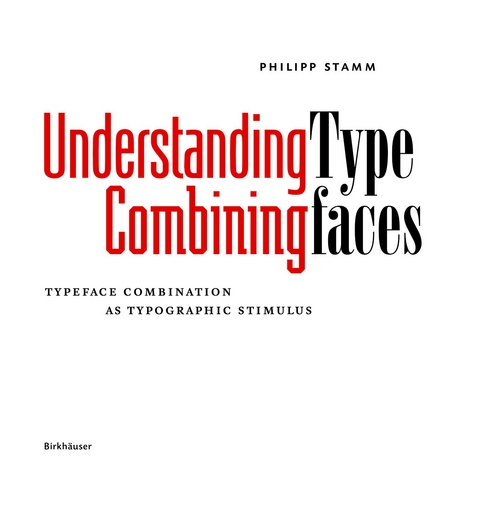
Understanding – Combining Typefaces
Typeface combination as a stimulus in typography
Die Schriftmischung ist eine der großen Herausforderungen und gleichzeitig ein steter Reiz für Typografen und Gestalter: Soll sie opulent, nur begrenzt oder am besten gar nicht stattfinden? Welche Schriften harmonieren miteinander, welche nicht? Welche ergänzen sich, lassen sich gar gegenseitig steigern? Die Fachliteratur bietet da wenig Hilfestellung. Dieses Handbuch zeigt, dass sich für das Mischen von Schriften Kriterien bestimmen lassen. Es vermittelt durch das detaillierte Betrachten der Schriftgestalt und eine erneuerte Schriftklassifikation ein vertieftes Verständnis für die Vielfalt an Schriftformen und erarbeitet durch die systematische Analyse von Analogie und Kontrast die dringend benötigten Erkenntnisse zum Kombinieren von Schriften. Ein unverzichtbares Standardwerk für Typografen und Grafikdesigner.
Philipp Stamm, Professor für Schriftgestaltung und Typografie, Hochschule für Gestaltung und Kunst, Basel.